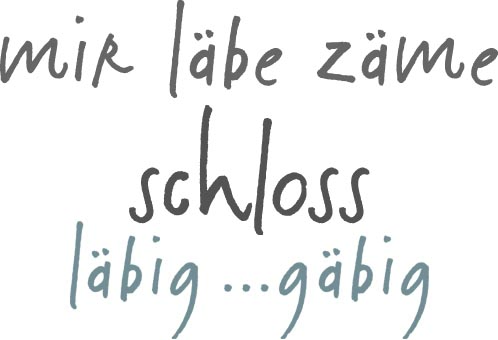
Wer kennt den Font "Eva Handschrift"?
Wer kennt die Schrift "Eva Handschrift"
Ich suche sie seit längerer Zeit, aber niemand kann mir weiter helfen. Mein Grafiker liefert mir zwar auf Anfrage einzelne Wortfetzen (siehe Beispiel), aber um arbeiten zu können, benötigte ich den Schriftsatz. Auch Linotype konnte nicht helfen. Vielleicht jemand im Forum? Vielen Dank!
das sieht nach einer digitalisierten Handschrift aus, deren Verursacherin heißt wahrscheinlich Eva. So was ist normalerweise nicht käuflich zu erwerben …
Dann nimm einfach eine andere … hier findest du unzählige Handschriftenfonts, da sollte der eine oder andere sehr ähnlich dabei sein.